Axialsatz
Typografischer Terminus für einen symmetrischen Flattersatz, eine gleichmäßige und spiegelbildliche Schriftsatzart, dessen Zeilenmitte exakt an der Mittelachse einer Seite bzw. einer Kolumne ausgerichtet ist; auch als »Mittelachssatz«, »Zentrierter Satz«, »Gemittelter Satz« oder »Symmetrischer Flattersatz« 1) bezeichnet. Etymologisch aus dem altgr. »axis« für »Achse«.
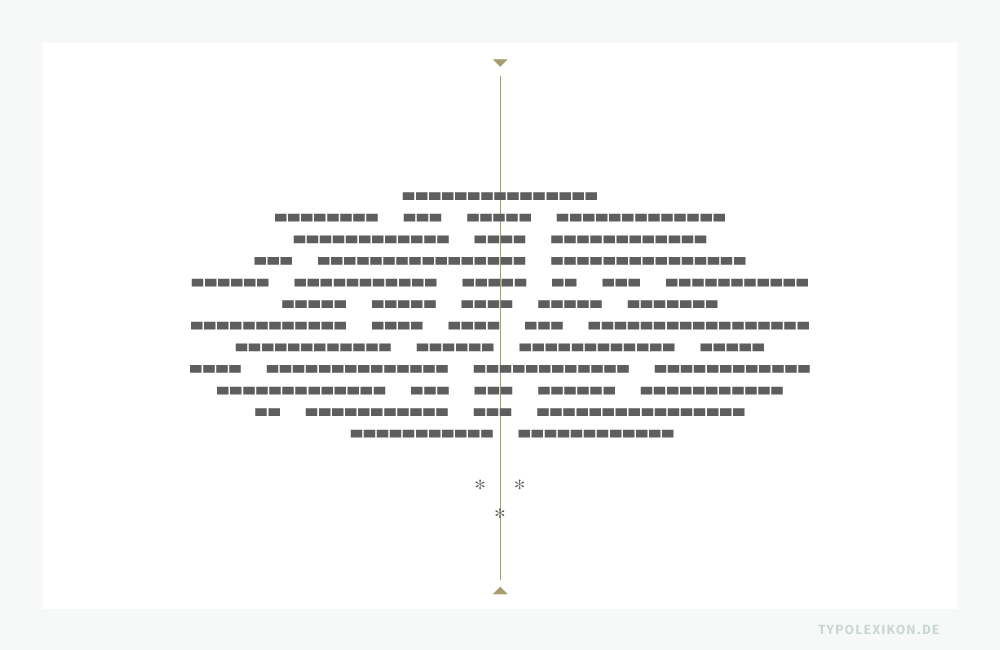
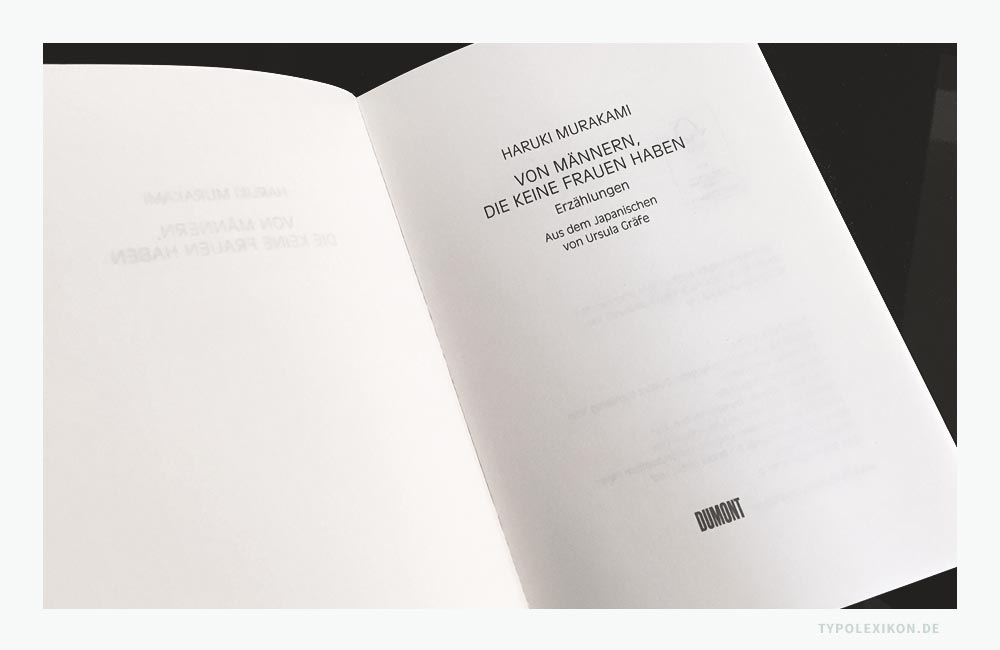
Axialer Satz 2) 3) findet beispielsweise bei Büchern in der Titelei oder als Kolumnenabschluß (Spitzsatz) oder bei Zeitungen und Magazinen als Headlines oder in Einleitungen Anwendung. Er wird auch gerne im klassischen Gedichtsatz (Lyrischer Flattersatz), bei Aphorismen und Zitaten sowie in der Werbe- und Gebrauchstypografie, beispielsweise bei Einladungskarten oder Briefpapieren verwendet.
| ↑1 | Anmerkung: »Symmetrisch« aus dem altgr. »symmetria« für »Ebenmaß« zu »symmetros« für »gleichmäßig«. |
| ↑2 | Tipp: Der Umbruch eines Axialsatzes muss immer handkorrigiert werden. |
| ↑3 | Tipp: Axialsatz ist grundsätzlich für den Mengenschriftsatz ungeeignet. |